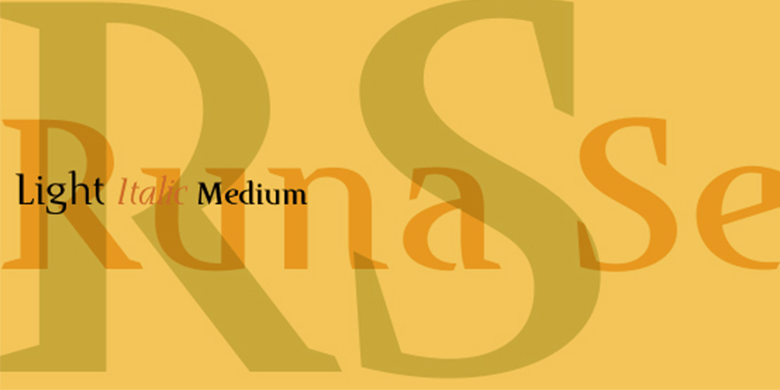
Runa Serif™
品牌:Monotype
设计师:
Lennart,Hansson
发行时间:2009
分类:
衬线体
瑞典设计师Lennart Hansson从20岁就开始设计字体,从那以后,他出色的书法作品就在世界各地展出。Hansson以其字体Runa Serif赢得了哥本哈根北欧字体大赛(Nordic Typeface Competition),这款字体的灵感来自于古代Viking runes的形式。<br><br>
Swedish designer Lennart Hansson began designing letterforms at the age of 20, and since then his exceptional calligraphic artwork has been on exhibit throughout the world. Hansson won the Nordic Typeface Competition in Copenhagen for his typeface Runa Serif, inspired by the forms of ancient Viking runes.